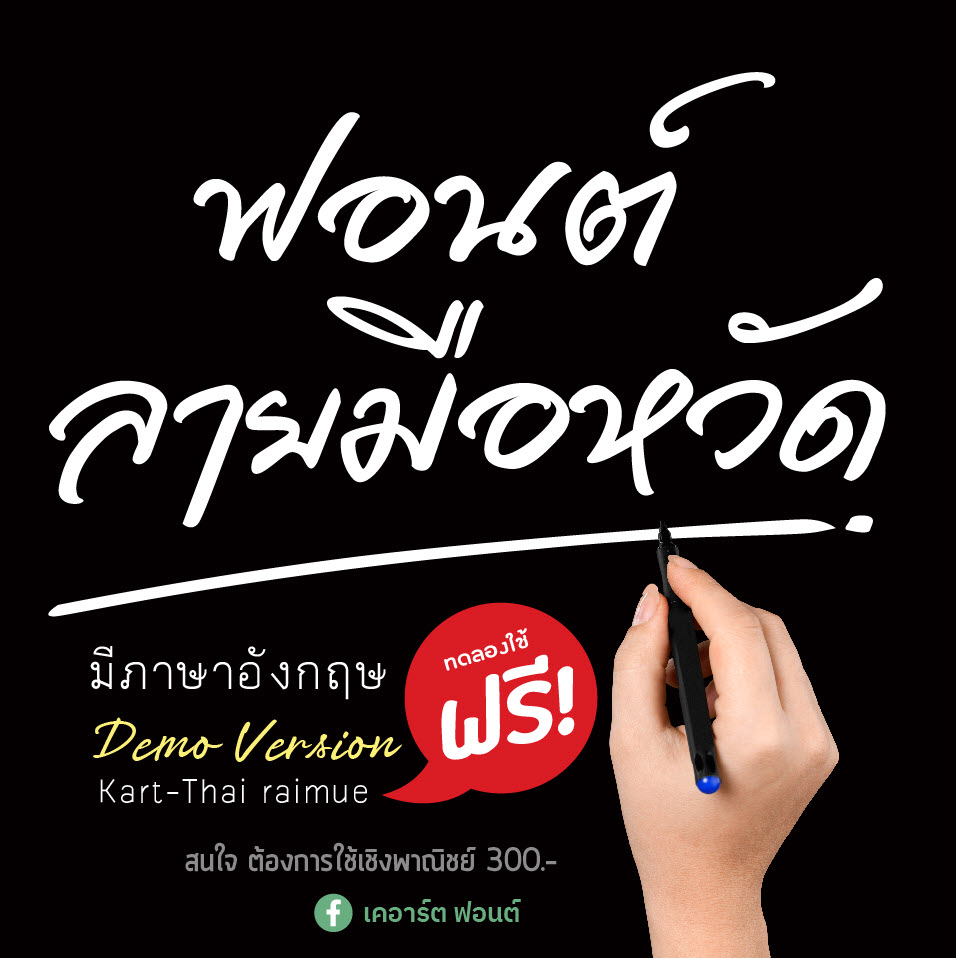
เคอาร์ตลายมือ (Kart-Thai raimue)
เคอาร์ตลายมือ (Kart-Thai raimue) เป็นฟอนต์ที่เขียนขึ้นจากความชอบลายมือตั้งใจเขียนมานานปรับแก้เพราะการเป็นฟอนต์ที่ต้องหลบหางเป็นอะไรที่ยาก